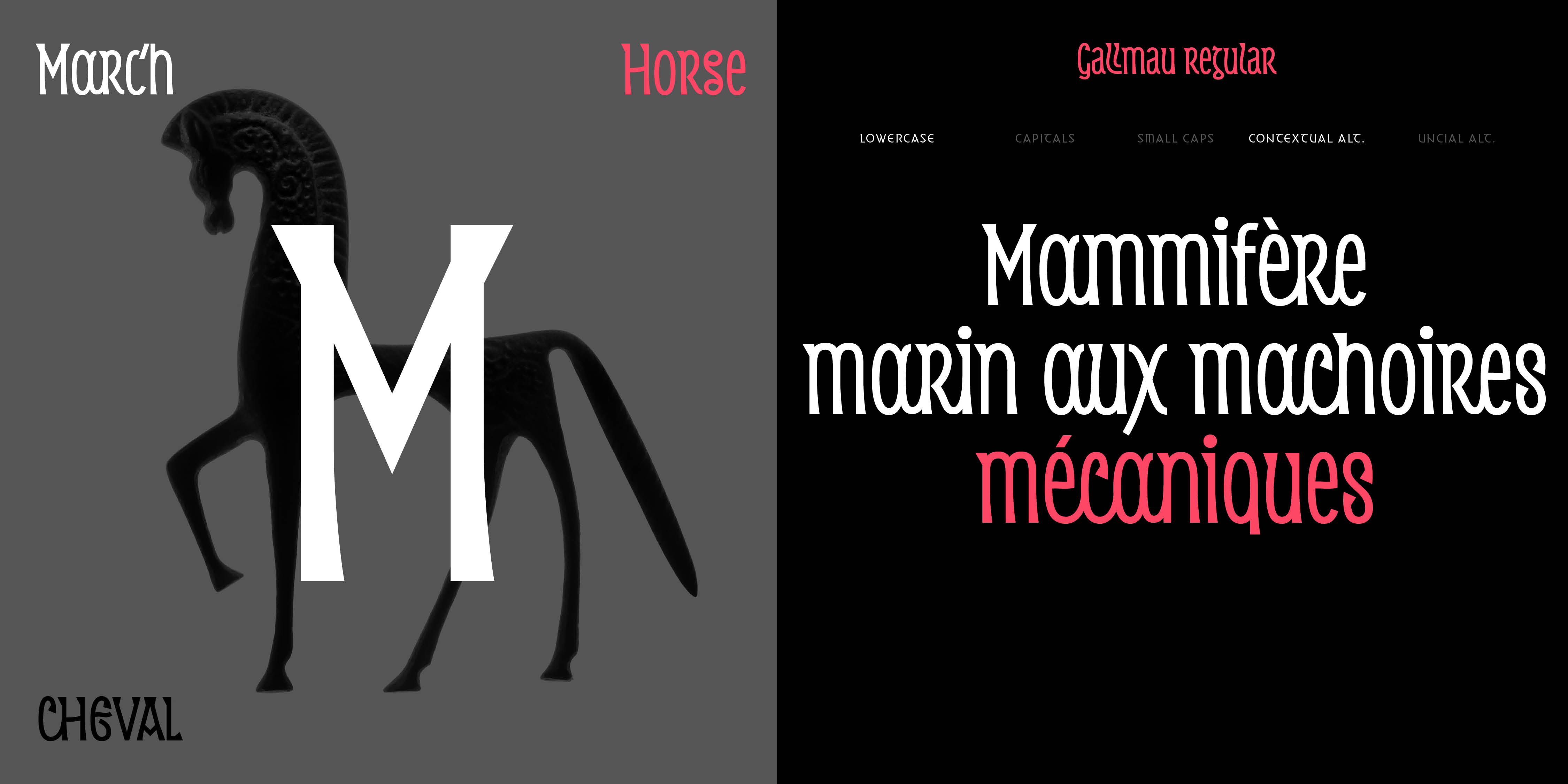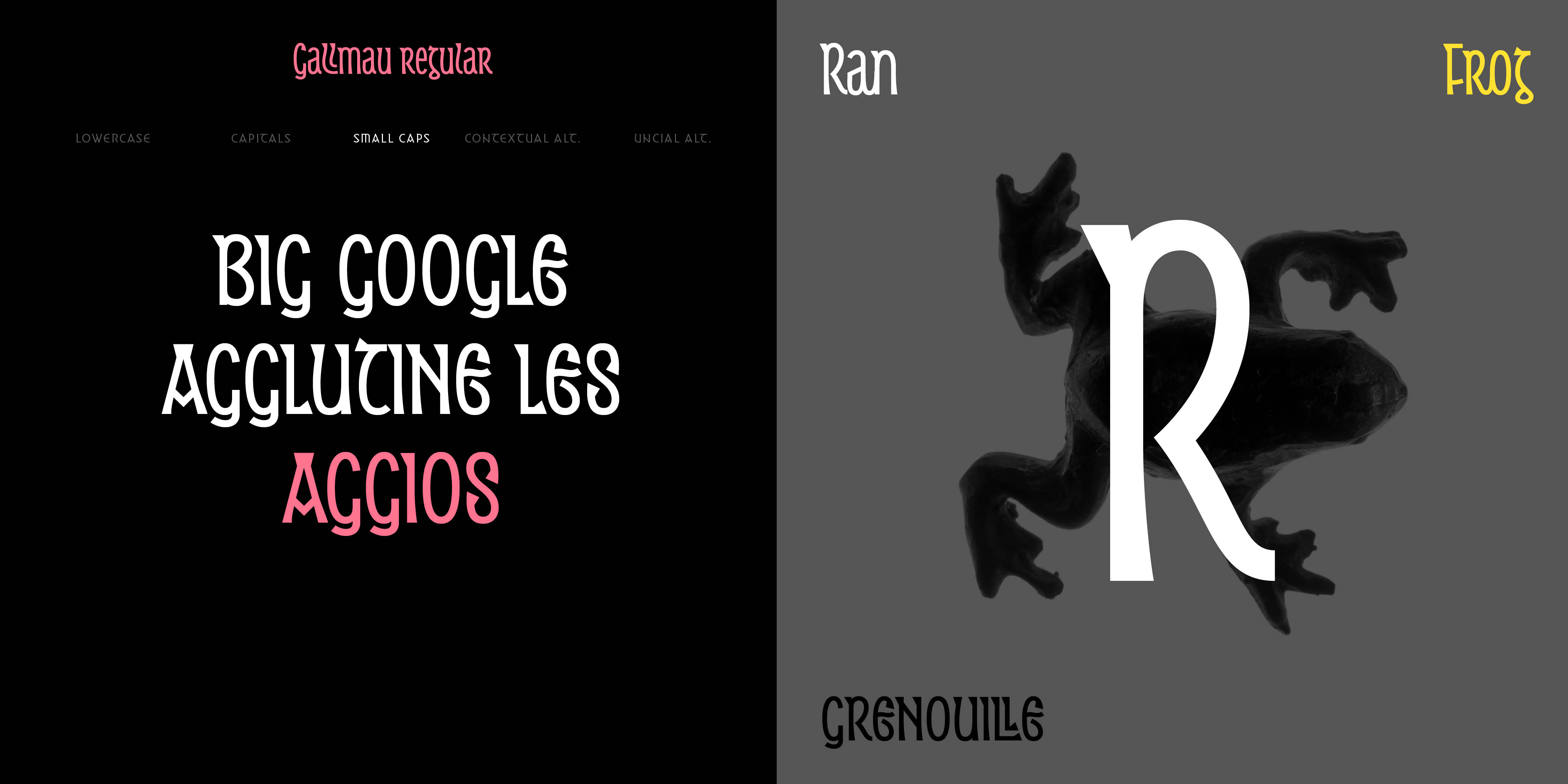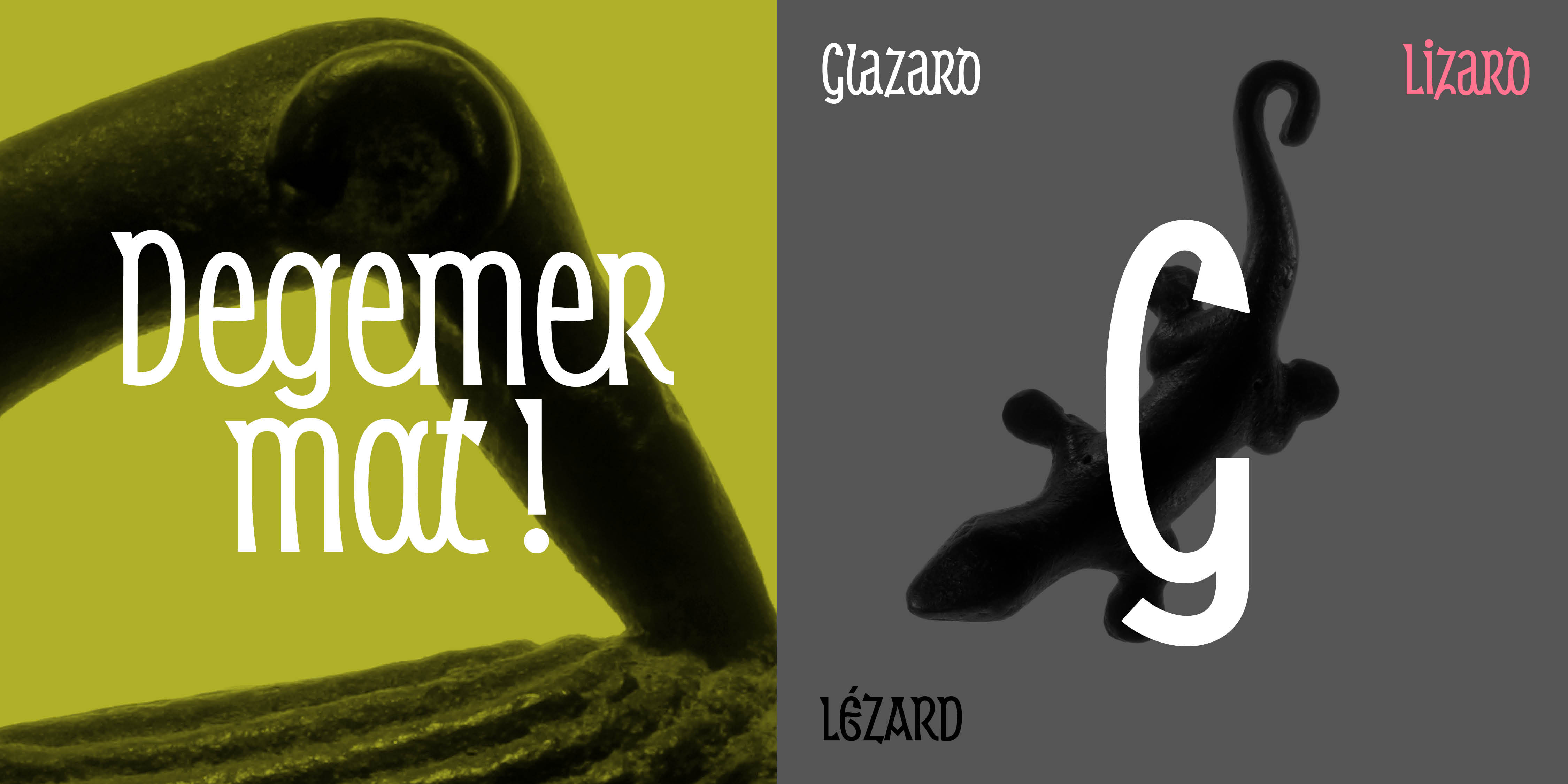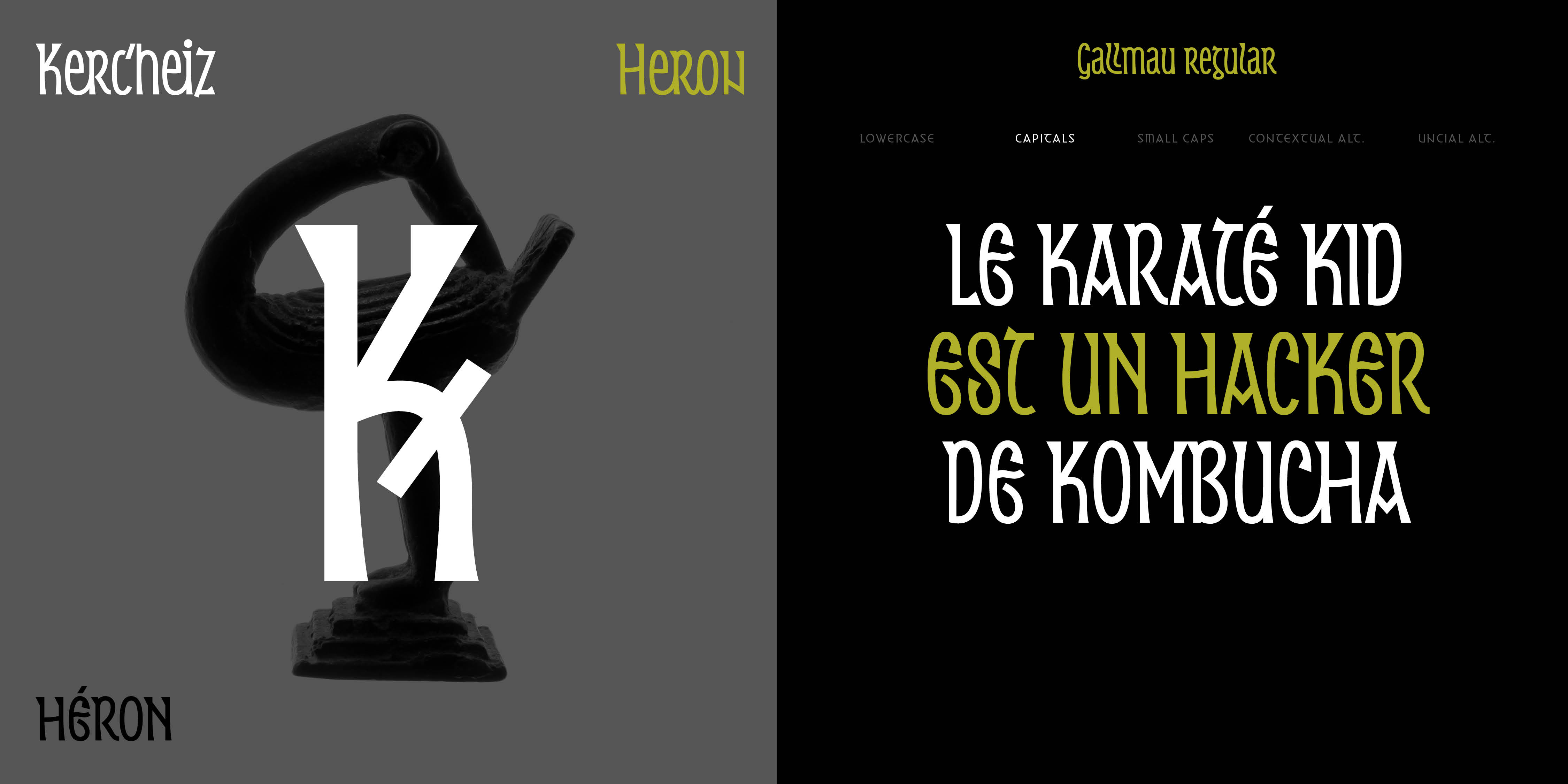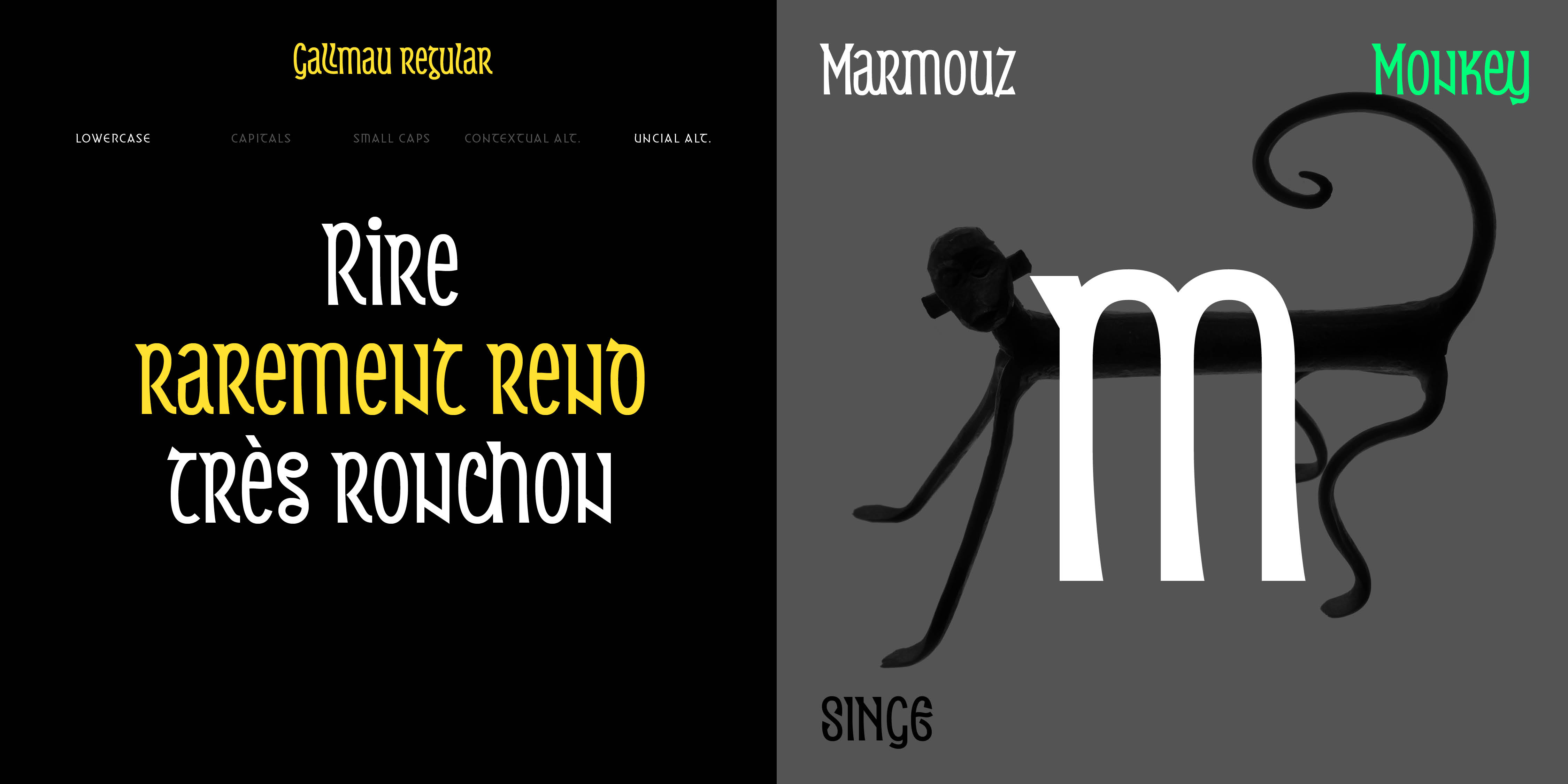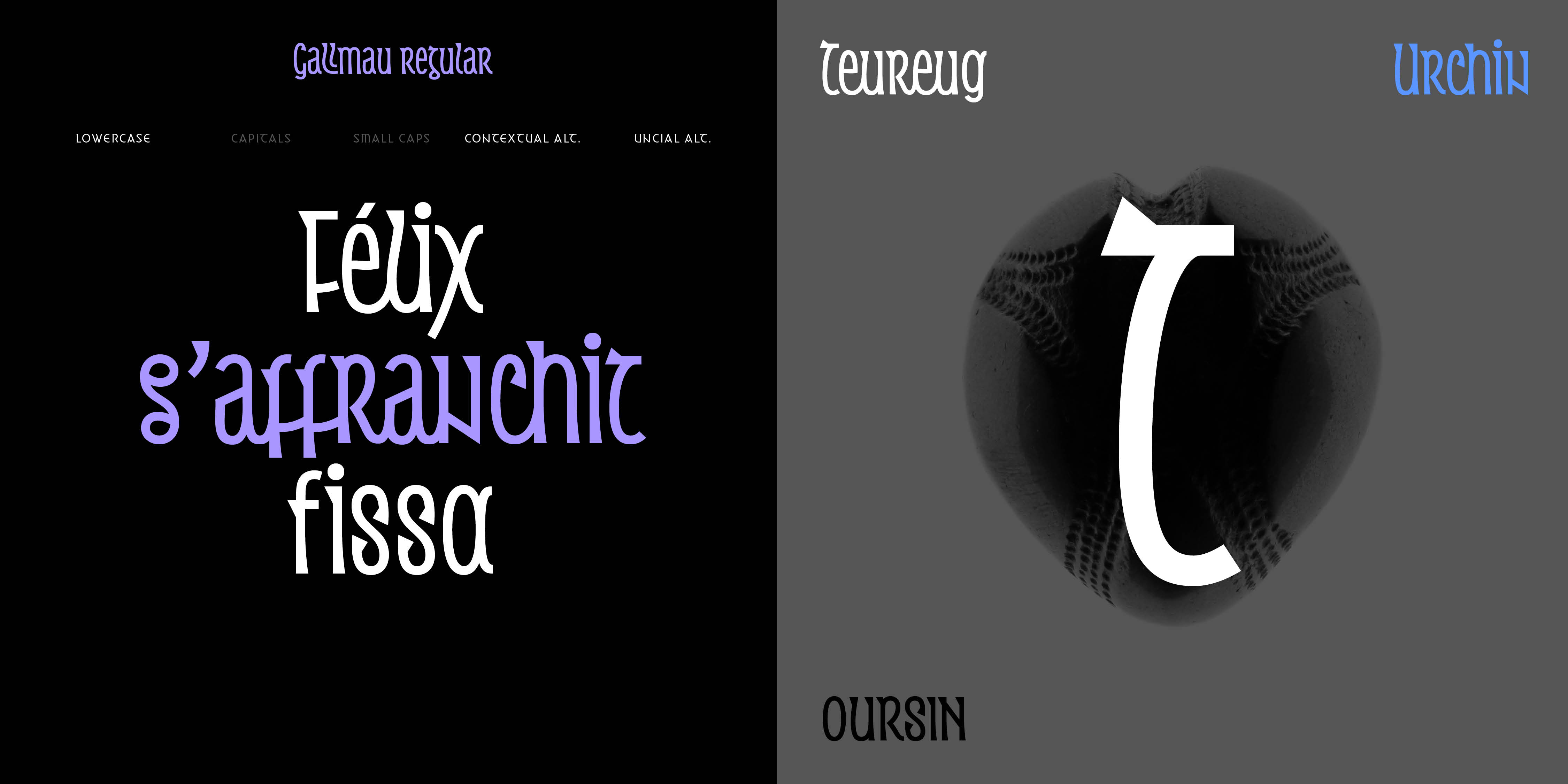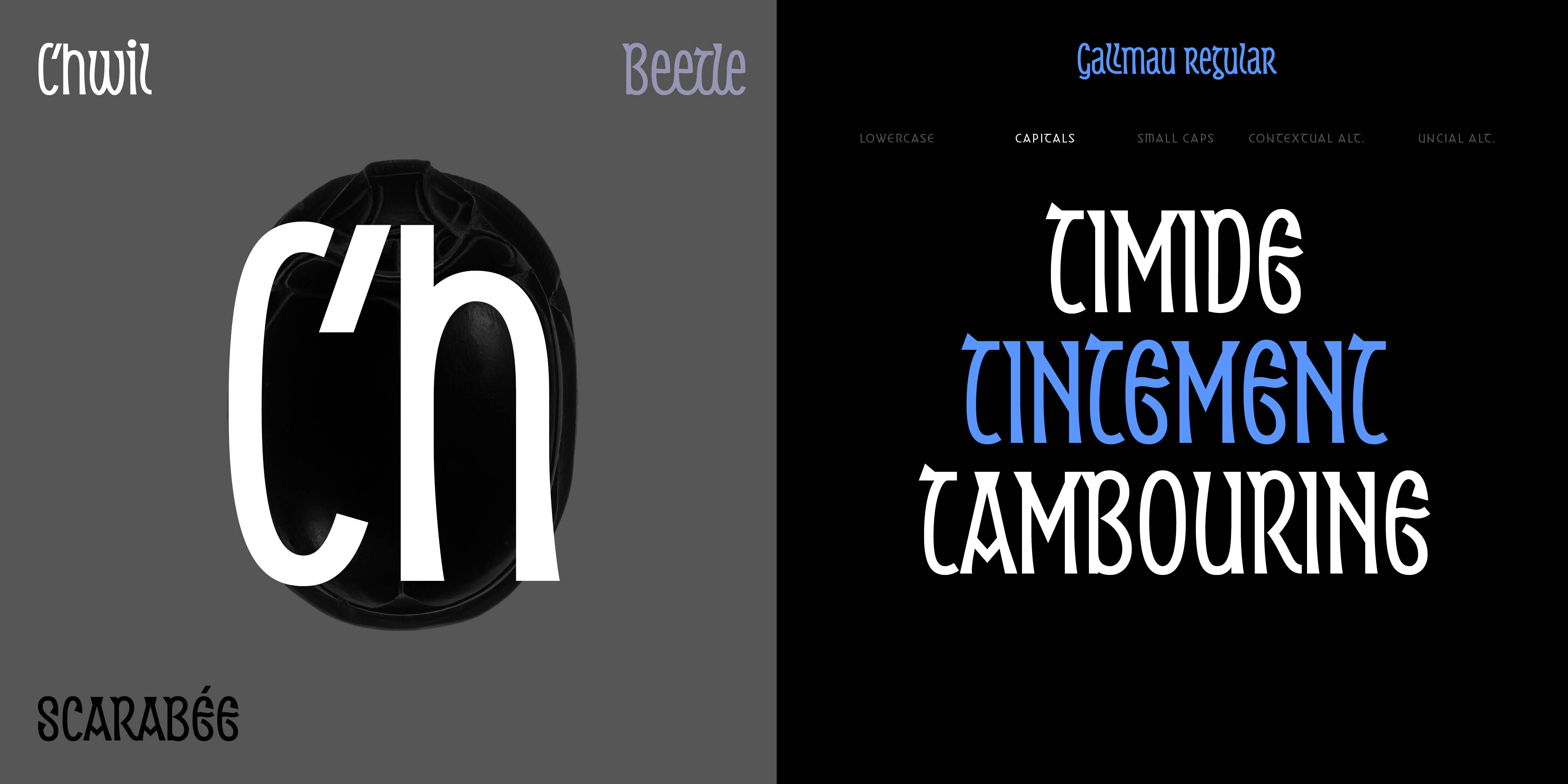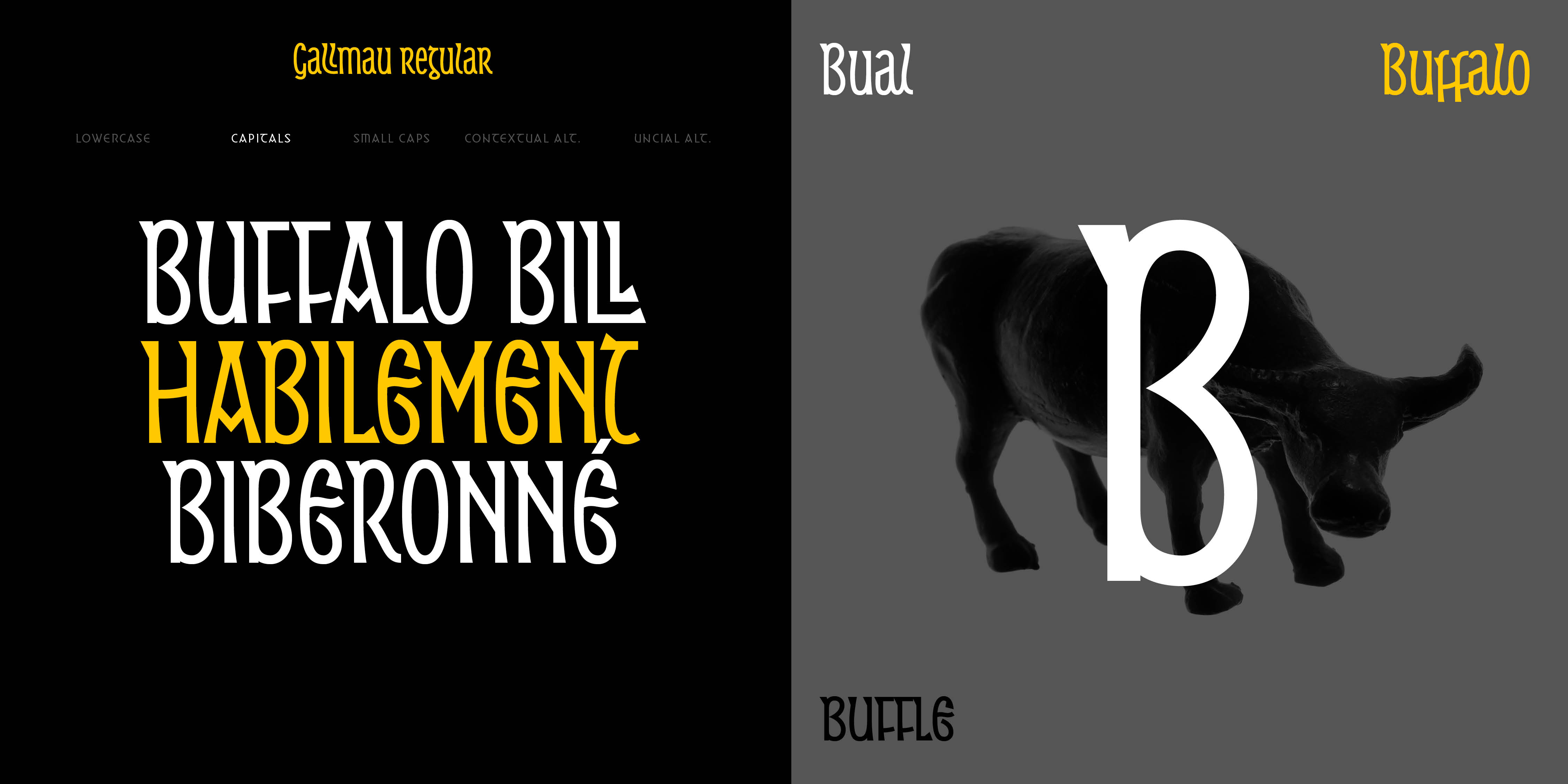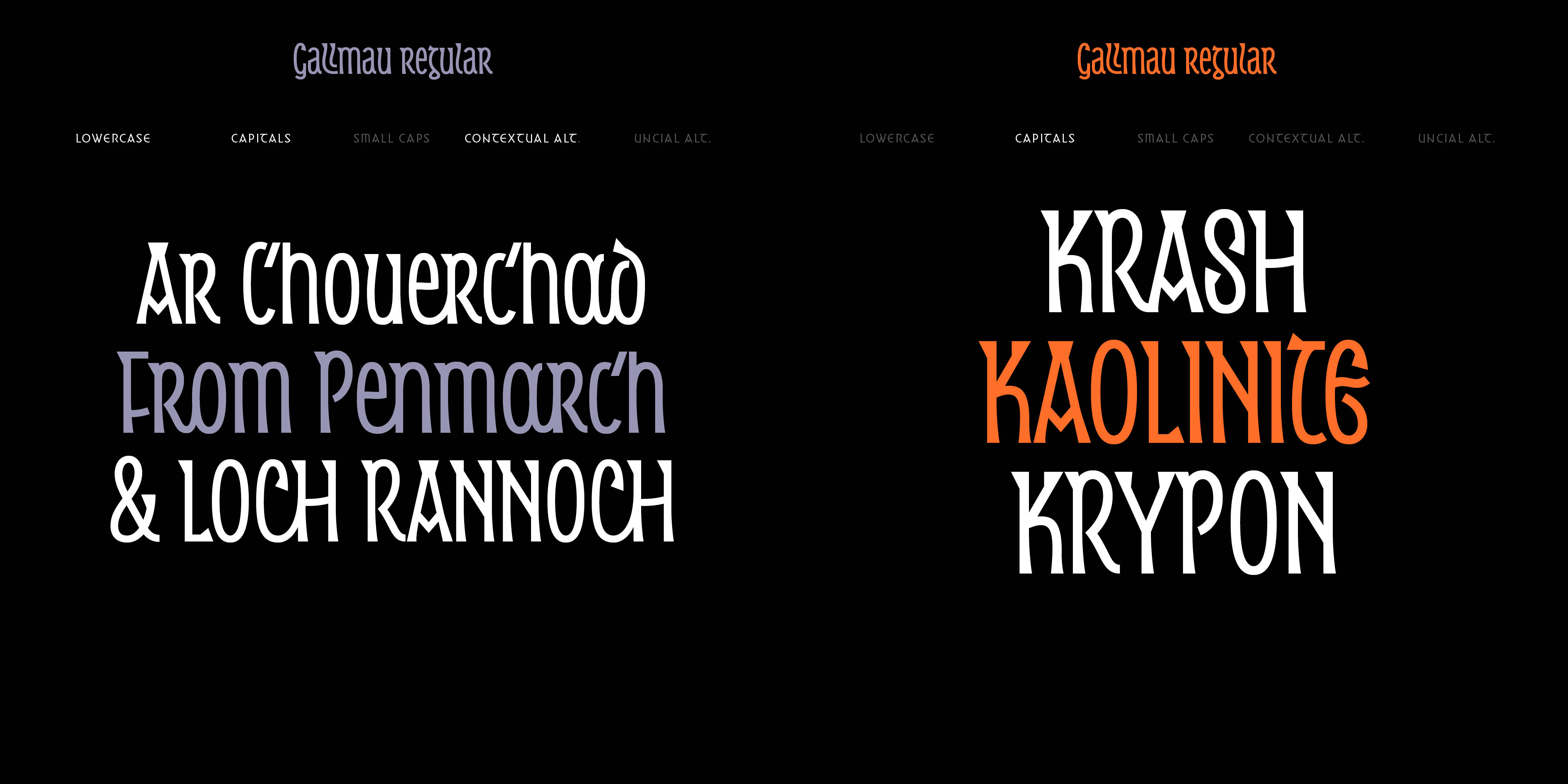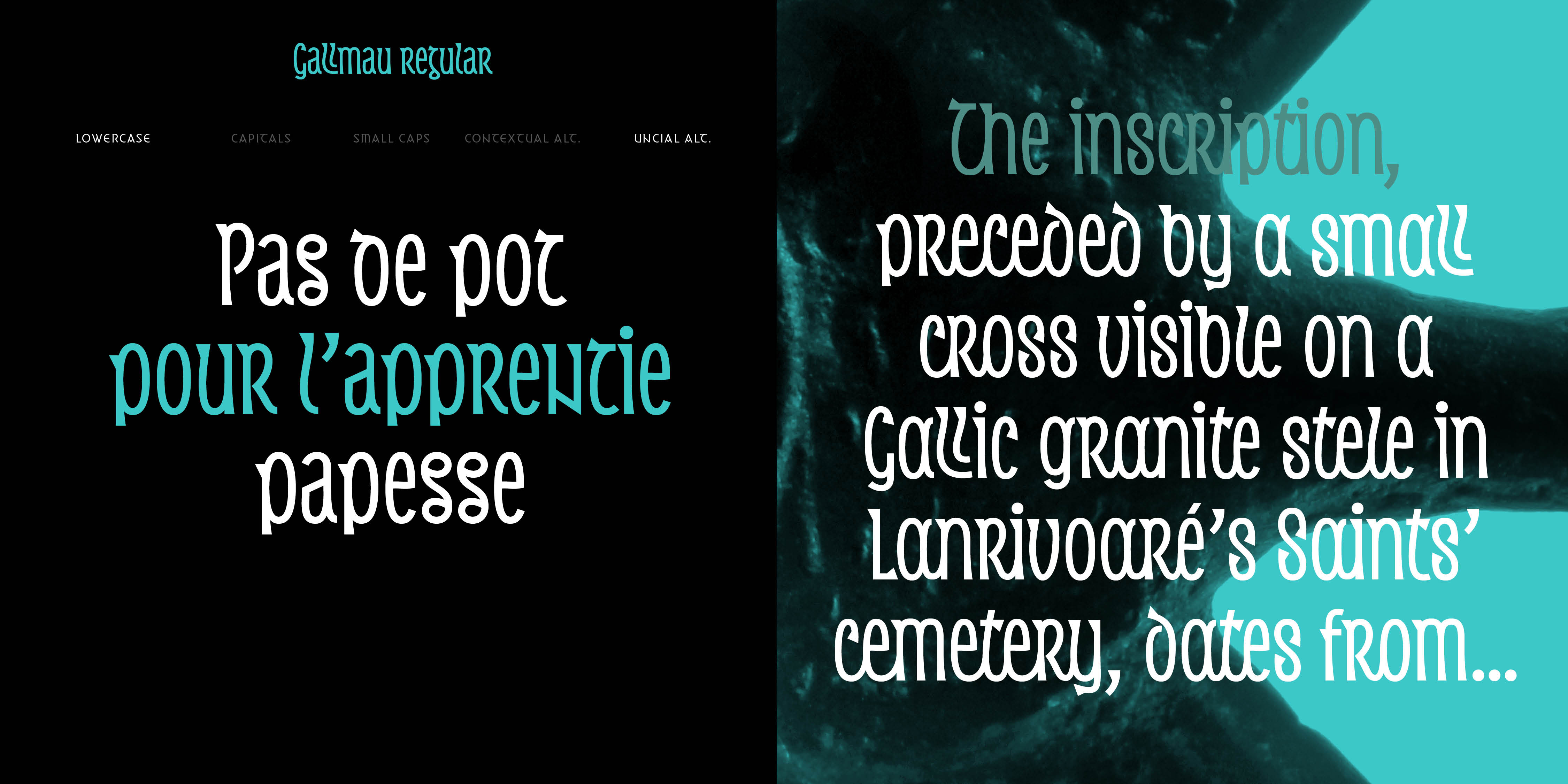
Gallmau
GALLMAU
Le Gallmau est une interprétation typographique libre de l’onciale que l’on observe sur les manuscrits enluminés irlandais et anglais à partir du VIIe siècle. Les moines ne se contentent pas de recopier l’onciale romaine, ils créent une écriture propre, la semi-onciale insulaire, qui intègre à l’alphabet latin des influences de l’art païen celte et anglais. Parmi les plus beaux manuscrits qui nous sont parvenus, le Livre de Durrow (664–700), les Évangiles de Lindisfarne (700) et le Livre de Kells (Iona et Kells 800). Les signes partagent la même hauteur, le tracé général est fluide et certaines paires de lettres sont attachées, créant ainsi une remarquable régularité des lignes. De l’onciale, le Gallmau conserve les liaisons entre les signes et la possibilité de composer indifféremment avec des formes majuscules ou minuscules. En revanche, la chasse change – le module est plus étroit, permettant une composition plus compacte des mots – et les effets de pleins et déliés provoqués par la plume sont gommés au profit d’une graphie monolinéaire plus contemporaine.
GALLMAU
Gallmau a zo un displegerezh dieub eus an onkial a vez kavet e-barzh an dornskridoù kozh irwerzhonat ha saoz er VIIvet hag en VIIIvet kanved. Ar venec’h a zo aet pelloc’h eget eilañ an onkial roman, krouet a zo bet ganto o skritur dezho, an hanter-onkial enezat, ul lizherenneg latin awenet gant an arz pagan keltiek ha saoz. E-touez ar bravañ dornskridoù degouezhet betek ennomp e kavomp Levr Durrow (664–700), Avieloù Lindisfarne (700) ha Levr Kells (Iona ha Kells 800). An tresad a zo hever dre vras hag al lizherennoù a zo staget an eil d'eben en ur grouiñ ur reoliegezh dispar gant al linennoù. Eus an onkial e chom gant ar Gallmau nemet al liammoù etre an arouezioù hag ar fed gallout lizherennañ gant a bep seurt stummoù pennlizherennoù pe lizherennoù munut. Padal, ar c’henfeur a cheñch – ar mollad a zo gant foet strishoc’h evit lizherennañ gant ur mod start – hag an efedoù leun ha diliamm graet gant ar bluenn a zo diverket evit lakaat war wel ur skrivadur unlinennek kalz kempredeloc’h.
GALLMAU
Gallmau is a free typographic interpretation of the uncial found on Irish and English illuminated manuscripts from the 7th century onwards. The monks not only copied the Roman uncial, but also created their own script, the insular half-uncial, which incorporated influences from pagan Celtic and English art into the Latin alphabet. Among the finest surviving manuscripts are the Book of Durrow (664–700), the Lindisfarne Gospels (700) and the Book of Kells (Iona and Kells 800). The signs share the same height, the general layout is fluid and certain pairs of letters are attached, creating a remarkable regularity of lines. From the uncial, Gallmau retains the links between signs and the possibility of composing indifferently with upper or lower case forms. On the other hand, the stroke changes – the module is narrower, allowing to set the words in a compact way – and the thick & thin stroke effects caused by the quill are erased in favor of a more contemporary monolinear script.